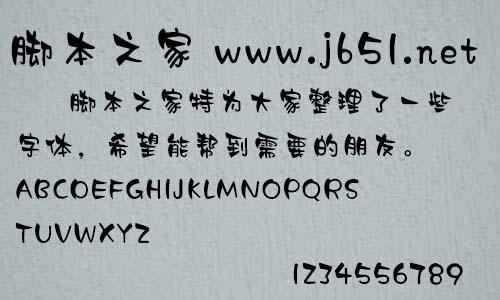
方正翹萌體字體由方正字庫出品的一款手繪字體,該筆觸較為粗實,字體書寫俏皮可愛,具有很好的視覺感,適合應用于藝術設計、平面宣傳設計、網(wǎng)頁設計,書法字帖等領域。
方正翹萌體是一款創(chuàng)意手繪字體,設計秉承左高右低、左粗右細的風格特點,通過粗細、方圓的合理搭配,呈現(xiàn)出靈活且平衡的字體結構。整體字形活潑可愛,除常見產(chǎn)品包裝、影視后期外,尤其適用于少兒類、綜藝類和趣味性產(chǎn)品使用。